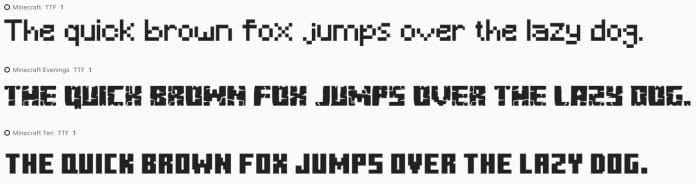
Font Chữ Minecraft Việt Hóa: Đánh Bại Lỗi Hiển Thị Ô Vuông, Tăng Tốc Thiết Kế Cho Mọi Dự Án Gaming
Bạn đã quá mệt mỏi với việc gõ tiếng Việt cho các thiết kế Minecraft và chỉ nhận lại những ô vuông vô hồn (□□□)? Đã đến lúc chấm dứt sự thiếu chuyên nghiệp đó. Poster.vn mang đến giải pháp tối thượng: bộ “Font chữ Minecraft Việt Hóa” hoàn chỉnh, được chế tác tỉ mỉ đến từng dấu câu. Đây là công cụ không thể thiếu cho các YouTuber, Streamer, nhà thiết kế và quản lý server Minecraft tại Việt Nam, giúp bạn tiết kiệm hàng giờ làm việc và tạo ra những sản phẩm nhất quán, đẹp mắt.
- Giải quyết triệt để vấn đề Việt Hóa: Đây là lý do cốt lõi và quan trọng nhất. Trong khi các font Minecraft miễn phí trên mạng thường xuyên bị lỗi ký tự tiếng Việt, font của chúng tôi đã được đội ngũ chuyên gia Việt hóa một cách hoàn chỉnh. Mọi ký tự đặc biệt (ă, â, đ, ê, ô, ơ, ư) và tất cả các dấu thanh (huyền, sắc, hỏi, ngã, nặng) đều được thiết kế lại theo đúng phong cách pixel-block đặc trưng. Bạn sẽ không bao giờ phải thấy những ô vuông đáng ghét hay phải tự tay “chế” dấu một cách thủ công nữa.
- Đảm bảo sự chuyên nghiệp và nhất quán tuyệt đối: Sử dụng một font chữ bị lỗi hoặc chắp vá khiến thiết kế của bạn trông rẻ tiền và thiếu chuyên nghiệp. Font Minecraft Việt Hóa của chúng tôi đảm bảo mọi con chữ, từ tiêu đề thumbnail YouTube, banner quảng cáo server cho đến nội dung trên áo thun merchandise, đều có một vẻ ngoài đồng nhất, đúng chuẩn phong cách Minecraft, giúp nâng cao uy tín và hình ảnh thương hiệu của bạn hoặc khách hàng.
| Hỗ trợ Tiếng Việt | Việt hóa đầy đủ 100%. Tất cả ký tự và dấu thanh tiếng Việt được thiết kế tỉ mỉ, đồng bộ với phong cách gốc. Gõ là được, không lỗi, không hiển thị ô vuông. | Thường xuyên bị lỗi ký tự, thiếu dấu, hoặc các dấu thanh được thêm vào một cách cẩu thả, sai vị trí, phá vỡ cấu trúc font. Hiển thị ô vuông (□) là vấn đề phổ biến nhất. |
| Chất lượng & Độ sắc nét | Chất lượng cao, các cạnh pixel sắc nét, rõ ràng ngay cả ở kích thước lớn. Font được tối ưu hóa để hiển thị tốt trên cả màn hình và các sản phẩm in ấn. | Chất lượng không đồng đều. Nhiều font miễn phí được tạo ra bằng các công cụ tự động, dẫn đến các cạnh bị mờ, pixel không đều, trông thiếu chuyên nghiệp khi phóng to. |